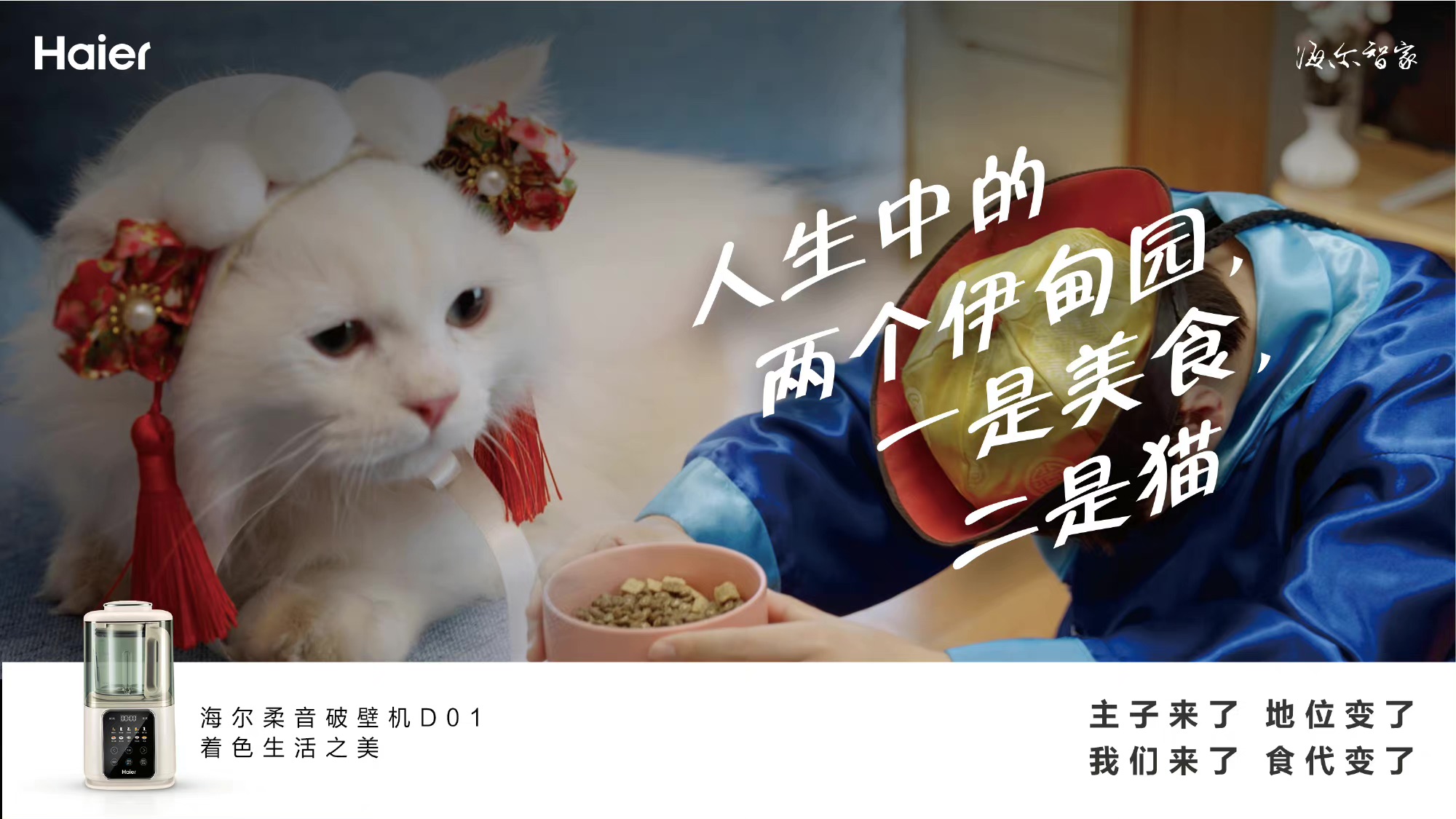
方正FW筑紫古典L明朝
Fontworks,方正字库
这是「筑紫字体」明朝体系列中最富情趣的一款字的大字风格。筑紫古典明朝保留了汉字本身造型的美感,能令人感受到翻阅金属活字时代油墨浓郁飘香页面时的情趣。排出的文字极具呼吸的空间,具有以往明朝体所没有的美感。这套字的特征是其紧凑的中宫和舒展的撇捺,在设计中不强调明朝体的方块感,而是重视文字固有的造型和骨架。假名虽属于正统的风格,却独具其特有的表情。偏小的平均字面能在排版时体现出宽松的字距。将「筑紫古典S明朝」的字进行了放大处理,令排版上的字距显出更得更为现代。
筑紫書体の明朝体ラインナップの中で、最も風情豊かな書体の《Large Style》です。 筑紫アンティーク明朝は、漢字そのものが持っている形の美しさをそのままに、金属活字時代のインクが濃く香り立つページに遭遇した時のような風情の明朝体です。 文字組みした際に、呼吸をしながら読めるこれまでにはない美しい明朝体です。 漢字の狭いフトコロや左右ハライの伸びやかさが特徴で、明朝体特有の正方形をあまり意識しない文字固有の形・骨格を重視したデザイン。 仮名はオーソドックスなスタイルの中に表情をしっかり保たせたデザイン。文字の平均文字面が小さくゆったりとした字間の文字組みになります。 筑紫アンティークS明朝の文字を拡大し、組み版で文字間を現代的な見え方にさせた書体。